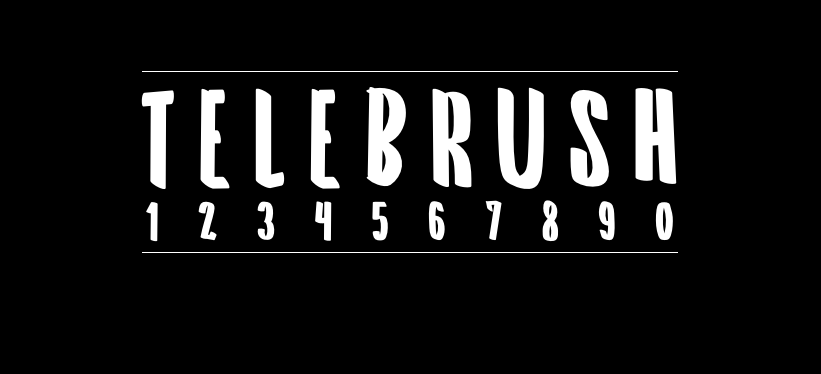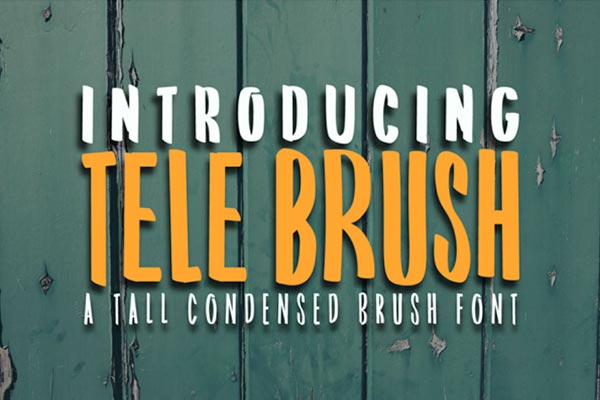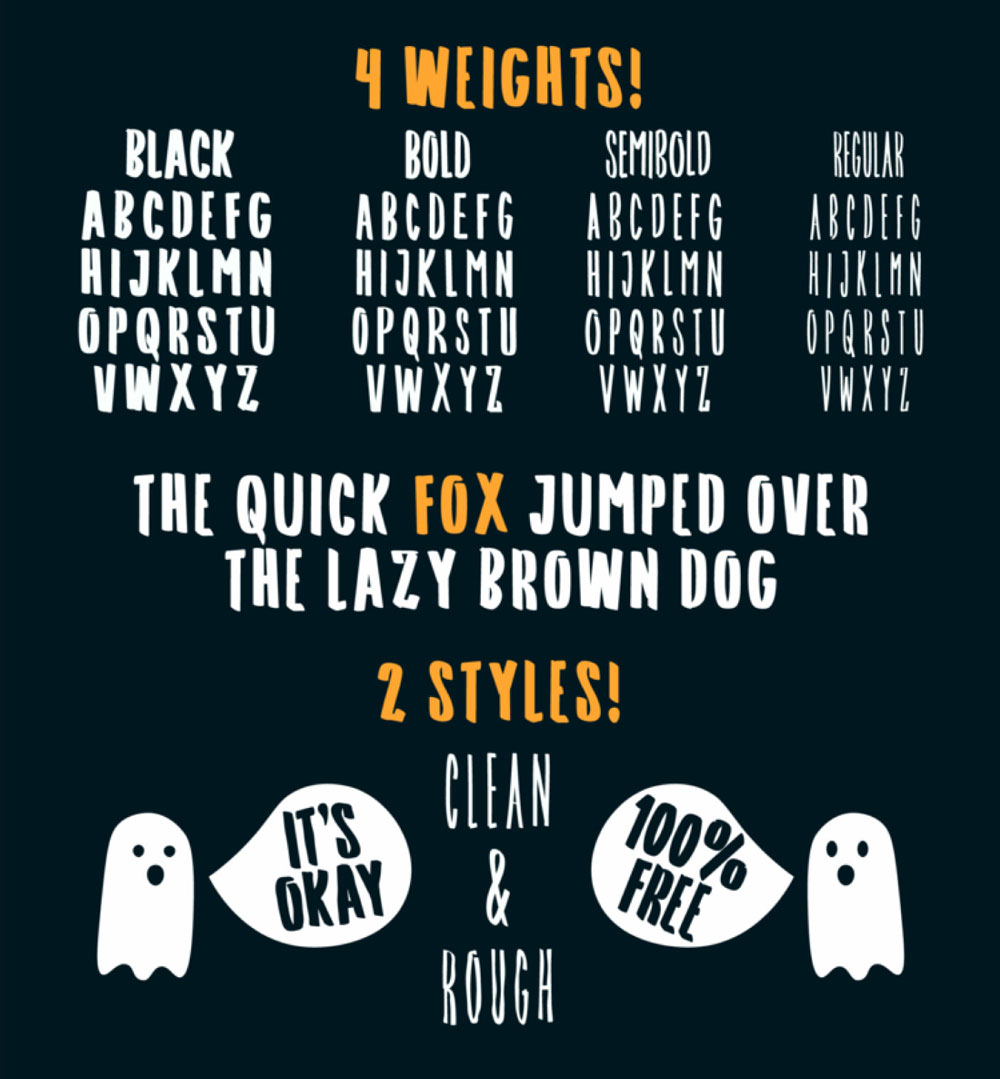
TeleBrush
TeleBrush字体介绍
TeleBrush是美国 Daler Mukhiddinov 创作的一款英文印刷字体,字如其名,该字体风格有点像刷在旧电话亭上的字体。TeleBrush拥有两种字形:Clean和Rough,Clean版本的字形比较干净,而Rough版本则在字体笔画上多一些毛糙的感觉,如果你希望更体现刷子的质感,可以考虑使用Rough版本。这两种字形都分别拥有4字重:Regular、Bold、Semibold、Black。
TeleBrush字体应用示例